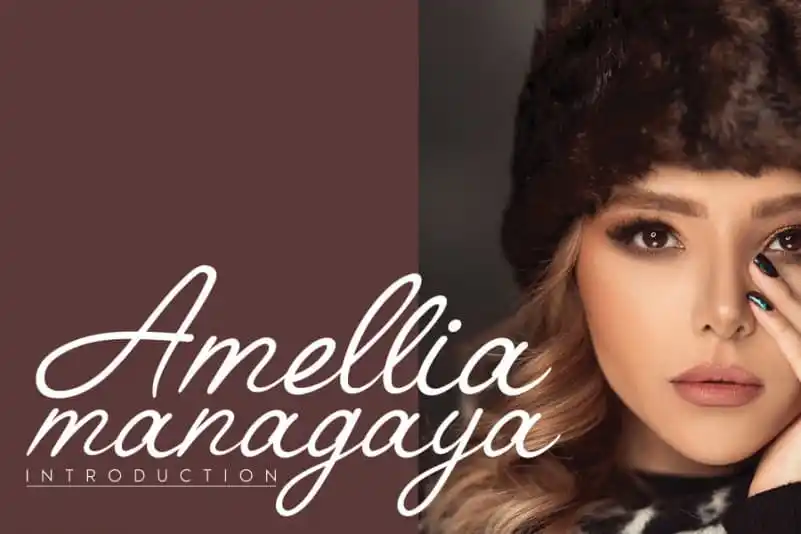
Amellia Handwritten Font – Download Grátis
A Amellia Handwritten Font é uma elegante tipografia para escrita a mão que se destaca pela sua simetria perfeita e equilíbrio. Embora seja perfeitamente adequada tanto para designs formais quanto não-formais, ela também oferece um toque delicado e refinado que faz dela uma escolha versátil em qualquer projeto. Ideal para adicionar um quê de personalidade aos seus trabalhos, a Amellia é perfeita para aplicações como logotipos, cartões de aniversário ou até mesmo revistas pessoais. Seja você designer gráfico, criador de conteúdo digital ou artista plástico, esta fonte será uma ótima adição ao seu leque. Seu estilo elegante e delicado torna-a perfeita para textos que buscam um toque especial, seja ele em designs simples ou complexos. Experimentar a Amellia é experimentar dar vida à sua criatividade de forma única e sofisticada.